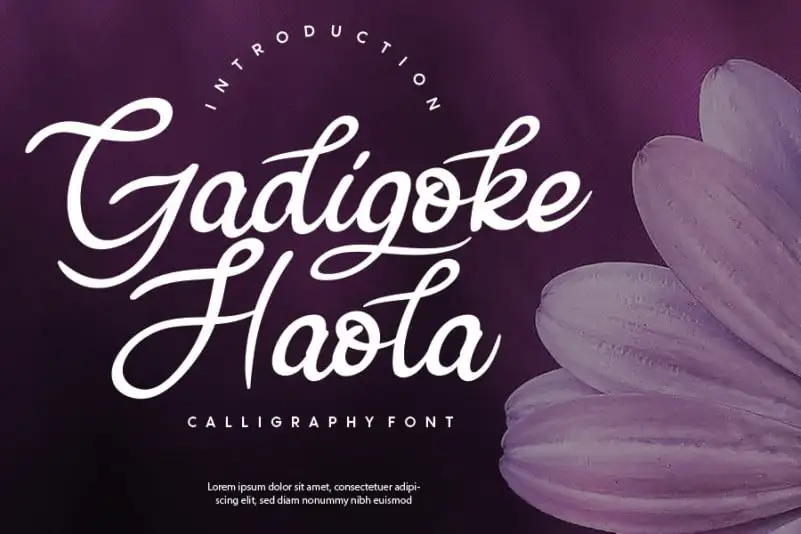
Gadigoke Handwritten Font – Download Grátis
A fonte Gadigoke Handwritten é uma escolha perfeita para designers amantes do estilo artesanal. Com seu charme elegante, esta fonte traz aos seus projetos um toque delicado e refinado que pode ser visto em cartões de agradecimento, convites de casamento, cartas personalizadas, cartazes de boas-vindas, logotipos e até mesmo cartões de visita. Suas linhas finas e suas curvas naturais criam um visual que se encaixa perfeitamente em qualquer design que busque uma mão escritora, trazendo ao seu trabalho um toque único e sofisticado. A Gadigoke Handwritten é a escolha ideal para aqueles que querem dar um novo encanto à sua arte digital.